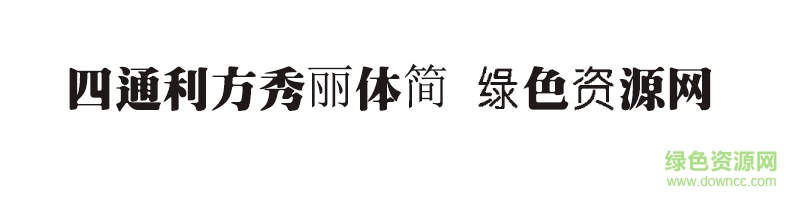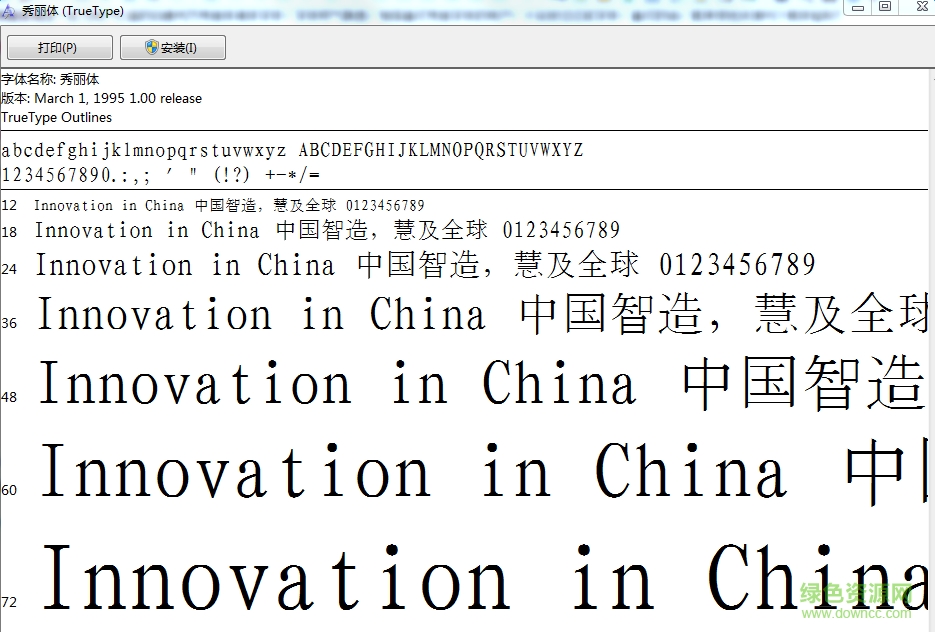
四通利方秀麗體簡是一款為用戶打造的四通利方秀麗體簡體字體,字體帥氣飄逸,相信喜歡秀麗字體的用戶,不會放過這款字體,喜歡的話,就來綠色資源網(wǎng)下載體驗唄!
四通利方秀麗體是一款不錯的手寫藝術(shù)字體,這款字體筆觸較為粗實,書寫端正大氣,重要的是可以免費商用,適合應(yīng)用于藝術(shù)設(shè)計、平面宣傳設(shè)計、網(wǎng)頁設(shè)計、海報設(shè)計等應(yīng)用。